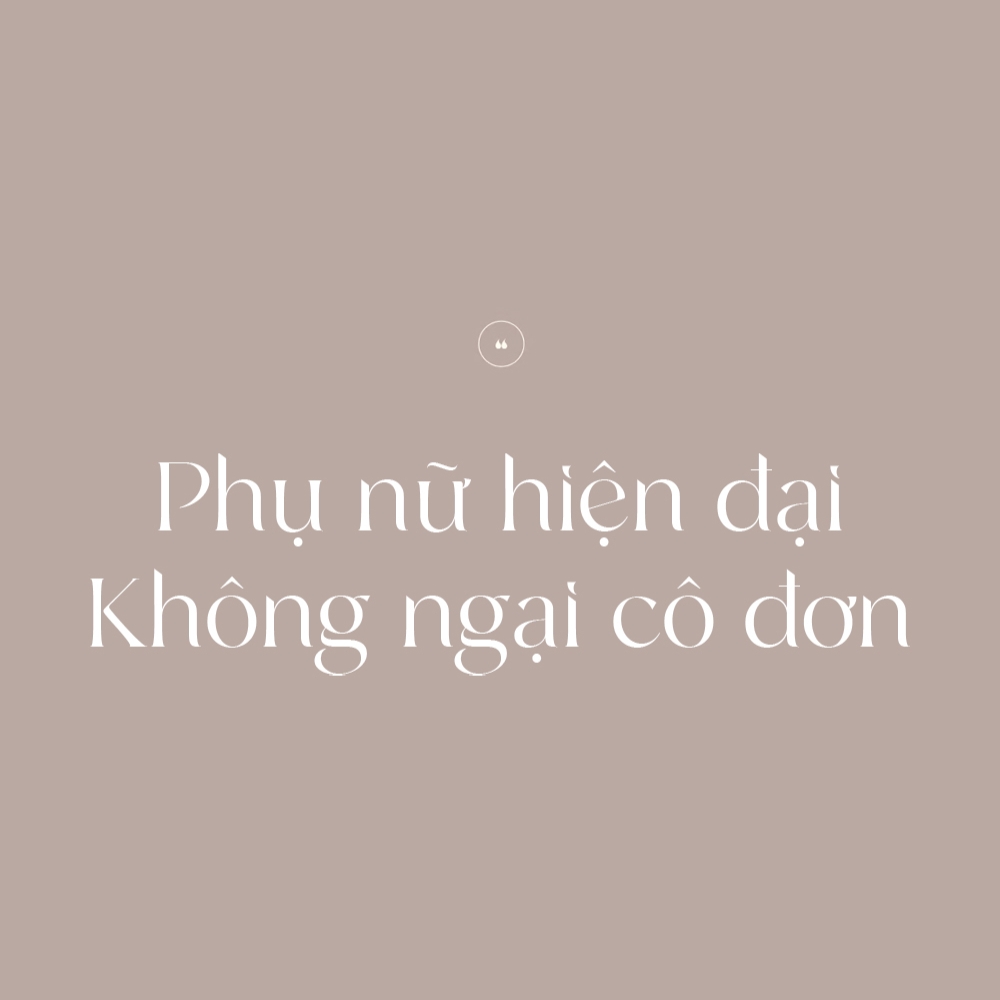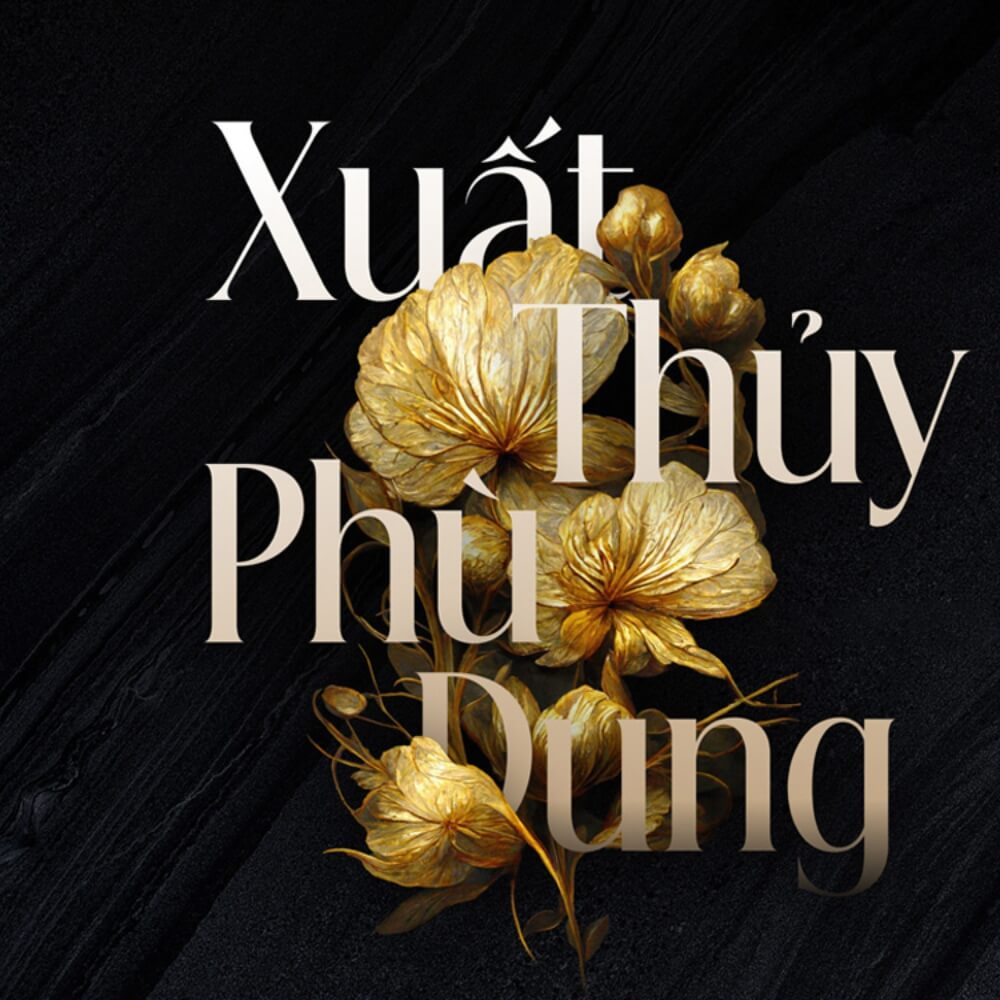
Tải 17+ font chữ tạp chí việt hóa miễn phí
Font chữ tạp chí việt hóa là font có phong cách chuyên nghiệp, thanh lịch được các tạp chí nổi tiếng sử dụng với đặc điểm dễ đọc, sang trọng, phù hợp cho thiết kế bao bì cao cấp, túi giấy thương hiệu và in logo sang trọng. Font tạp chí với nét chữ cân đối, tinh tế tạo cảm giác uy tín, chất lượng.
Ở bài viết này, In Viva giới thiệu font chữ tạp chí và các font miễn phí có phong cách tương tự Vogue, Time, National Geographic phù hợp cho thiết kế bao bì giấy và túi giấy chuyên nghiệp.
Font chữ tạp chí là gì?
Font chữ tạp chí là những font được các tạp chí in ấn lựa chọn để đảm bảo nội dung dễ đọc trong khi vẫn giữ vẻ thẩm mỹ cao. Khác với font dùng trên web, font tạp chí được tối ưu đặc biệt cho việc in trên giấy – nơi người đọc nhìn thấy từng chi tiết nhỏ.
Các tạp chí khác nhau chọn font khác nhau tùy đối tượng và tính cách thương hiệu. Tạp chí thời trang cao cấp thường chọn font có chân kiểu hiện đại với nét mảnh, tương phản cao – tạo cảm giác sang trọng. Tạp chí tin tức nghiêm túc ưa dùng font có chân cổ điển – tạo sự tin cậy. Tạp chí khoa học chọn font dễ đọc cho văn bản dài. Tạp chí đương đại có thể dùng font không chân hiện đại.
Font nổi tiếng của các tạp chí lớn:
• Vogue: Didot – font thanh lịch kiểu Pháp với tương phản nét cực cao, biểu tượng thời trang xa xỉ.
• Time: Times New Roman – font tin cậy, nghiêm túc đại diện cho báo chí chuyên nghiệp.
• Harper’s Bazaar: Didot và Bodoni – cùng họ font có chân hiện đại.
• National Geographic: Franklin Gothic – font không chân mạnh mẽ, rõ ràng.
• Tạp chí văn học: Caslon – font cổ điển thanh lịch cho nội dung nghiêm túc.
Đặc điểm font tạp chí phải dễ đọc ở nhiều kích thước – từ tiêu đề lớn đến chú thích nhỏ. Cần nhiều độ đậm khác nhau để phân cấp thông tin rõ ràng. Khoảng cách chữ và dòng được tính toán kỹ để văn bản dài dễ theo dõi.
Font tạp chí việt hóa giúp thiết kế sang trọng dễ đọc và chuẩn thẩm mỹ
Tên font
Phong cách tạp chí
Ứng dụng in ấn tốt nhất
Playfair Display
Tạp chí thời trang, thanh lịch. Túi giấy thời trang, bao bì mỹ phẩm cao cấp.
Libre Baskerville
Tạp chí tin tức, nghiêm túc. Bao bì giấy doanh nghiệp, túi giấy công ty.
Merriweather
Tạp chí văn học, dễ đọc. Bao bì giấy có nhiều thông tin, túi giấy sách.
Lora
Tạp chí phong cách sống đương đại. Túi giấy lifestyle, bao bì wellness.
Spectral
Tạp chí hiện đại, tinh tế. Bao bì giấy hiện đại, túi giấy boutique.
Crimson Text
Tạp chí học thuật, cổ điển. Bao bì giấy truyền thống, túi giấy nhà sách.
PT Serif
Tạp chí đa năng, chuyên nghiệp. Mọi loại bao bì giấy, túi giấy chuyên nghiệp.
Lưu ý về kích thước: Với chữ in trên bao bì giấy, túi giấy, kích thước tối thiểu nên từ 8 – 10 điểm để dễ đọc. Chữ quá nhỏ (dưới 8 điểm) khó đọc, đặc biệt là font có chân với nét mảnh.
Ứng dụng font tạp chí trong bao bì và túi giấy
Font chữ tạp chí mang lại nhiều lợi ích cho bao bì và túi giấy:
• Chuyên nghiệp, uy tín: Khi thương hiệu dùng font tạp chí trên bao bì, túi giấy, họ truyền tải thông điệp sản phẩm đáng tin, chất lượng cao.
• Dễ đọc tuyệt vời: Font tạp chí được thiết kế để đọc dễ dàng – quan trọng cho bao bì có nhiều thông tin sản phẩm, thành phần, hướng dẫn sử dụng.
• Sang trọng, tinh tế: Font có chân kiểu hiện đại như Didot, Playfair tạo liên tưởng đến tạp chí thời trang xa xỉ – giúp bao bì, túi giấy trông cao cấp hơn.
• Vượt thời gian: Font tạp chí không lỗi mốt – thiết kế bao bì, túi giấy dùng font này đẹp bền vững qua nhiều năm.
Font tạp chí xuất hiện trong nhiều sản phẩm:
• Túi giấy thời trang: túi kraft, túi couche cho thương hiệu thời trang, boutique cao cấp.
• Bao bì giấy mỹ phẩm: hộp skincare, hộp nước hoa, hộp makeup có nhiều thông tin thành phần.
• Túi giấy thương hiệu sang: túi giấy flagship store, concept store, showroom cao cấp.
• Bao bì giấy doanh nghiệp: hộp quà tặng doanh nghiệp, hộp sản phẩm B2B.
• Túi giấy lifestyle: túi giấy cho spa, wellness, organic shop.
• In logo lên bao bì, túi giấy: logo chữ thanh lịch cho thương hiệu cao cấp.
Font chữ tạp chí việt hóa mang phong cách thanh lịch chuyên nghiệp
Font tạp chí dễ in hơn font có nét quá mảnh. Tuy nhiên font có chân hiện đại (Didot-style) với nét rất mảnh cần: kích thước tối thiểu 10 điểm, giấy không thấm (couche, ivory), in offset chất lượng cao.